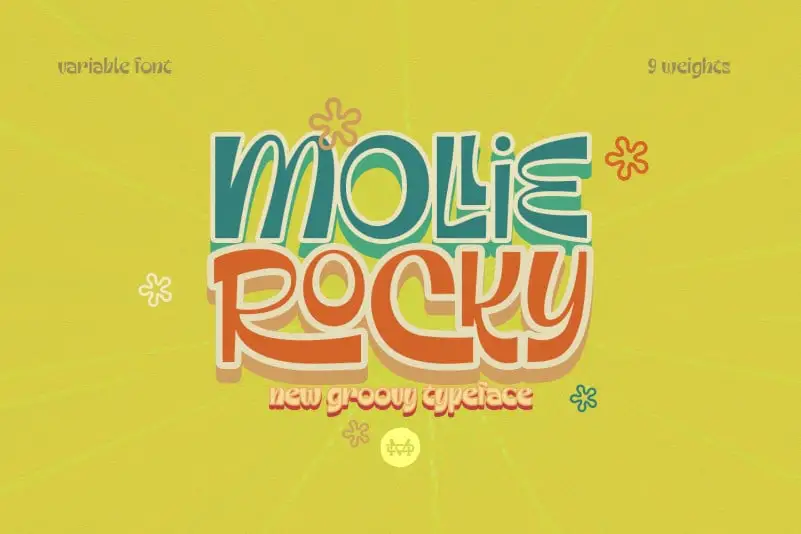
Mollie Rocky Display Font – Fonte Grátis
Mollie Rocky Display Font
A Mollie Rocky Display Font é uma escolha ideal para arquitetar o visual de qualquer projeto moderno e retro ao mesmo tempo. Desenvolvida pelo designer madeDeduk, esta família de fontes modernas e vibrantes tem um design tipográfico nostálgico que faz deliciosamente sua voz soar vintage sem perder a elegância moderna. As linhas grossas e finas das letras formam uma escrita retro única, criando um efeito impressionante. É perfeita para adicionar um toque de gôndola ao seu site ou marca digital. Com este estilo único, sua identidade visual terá a atenção necessária para destacar-se no meio de uma multidão. Não se limite à forma convencional, permita que sua fonte Mollie Rocky Display abraça o design moderno com as influências nostálgicas da era dos anos 80 e 90. A elegância do diseño moderno em contraste com a característica tipográfica retro faz dela uma escolha inteligente para qualquer projeto onde você deseja destacar sua identidade visual. Com Mollie Rocky Display Font, seu design será uma mistura de simplicidade e originalidade que chama atenção imediatamente.